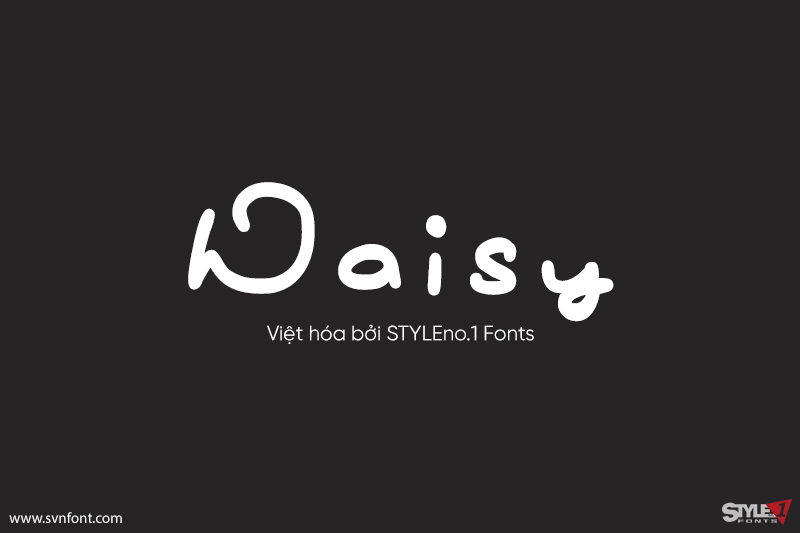
Tải Font Việt hóa SVN Daisy Miễn Phí: Tuyệt Chiêu Thiết Kế Tài Liệu Học Tập Chuyên Nghiệp
Trong thế giới thiết kế đồ họa và tài liệu học thuật, việc lựa chọn một Font Chữ phù hợp không chỉ giúp truyền tải thông điệp rõ ràng mà còn tạo nên dấu ấn thẩm mỹ riêng biệt. Đặc biệt đối với học sinh, sinh viên và giáo viên, những tài liệu cần sự hấp dẫn thị giác cao như bài thuyết trình hay luận văn tốt nghiệp, một bộ font đẹp là điều không thể thiếu. Hôm nay, chúng tôi sẽ giới thiệu chi tiết về Font Việt hóa SVN Daisy – một lựa chọn tuyệt vời cho mọi nhu cầu typography tiếng Việt.
Bộ font này đã nhanh chóng trở nên phổ biến nhờ sự kết hợp hài hòa giữa phong cách hiện đại và nét mềm mại, rất phù hợp cho các dự án sáng tạo. Việc sử dụng phiên bản đã được Việt hóa hoàn chỉnh giúp người dùng dễ dàng nhập liệu tiếng Việt với đầy đủ các dấu thanh mà không gặp lỗi hiển thị, đây là ưu điểm lớn so với các font quốc tế chưa được tối ưu.
Giới Thiệu Về Font Việt hóa SVN Daisy: Nét Chữ Mềm Mại Cho Mọi Thiết Kế
SVN Daisy thuộc nhóm font chữ script hoặc calligraphy nhẹ, mang lại cảm giác viết tay tự nhiên, thanh lịch. Nó được phát triển dựa trên bộ font gốc và được cộng đồng SVN (Style Việt Nam) tiến hành Việt hóa một cách tỉ mỉ. Mục tiêu của việc Việt hóa là đảm bảo font hiển thị hoàn hảo các ký tự đặc biệt trong tiếng Việt như ă, â, đ, ê, ô, ơ, ư mà vẫn giữ nguyên được tính thẩm mỹ và độ tương thích cao trên nhiều hệ điều hành và phần mềm khác nhau.
Font chữ này nổi bật nhờ các đường nét uyển chuyển, độ dày mỏng linh hoạt, tạo cảm giác sang trọng nhưng không quá cầu kỳ. Đây là lý do khiến Font Việt hóa SVN Daisy được ưa chuộng không chỉ trong thiết kế thiệp mời, bao bì mà còn trong các ấn phẩm giáo dục đòi hỏi sự tinh tế, từ các bài giảng cấp cao đến các ấn phẩm chuẩn bị cho kỳ thi tốt nghiệp THPT.
Đặc Điểm Nổi Bật Của Bộ Font SVN Daisy Gốc Và Phiên Bản Việt Hóa
Để hiểu tại sao SVN Daisy lại là lựa chọn hàng đầu cho các chuyên gia và học sinh đang chuẩn bị cho các kỳ thi hay dự án cuối cấp, chúng ta cần xem xét những đặc điểm kỹ thuật và thẩm mỹ của nó:
- Tính thẩm mỹ cao: Phong cách chữ viết tay, lãng mạn, rất phù hợp cho tiêu đề bài giảng, bìa sách, hoặc slide thuyết trình. Nó giúp tài liệu học tập trở nên sinh động và ít khô khan hơn.
- Khả năng ứng dụng linh hoạt: Mặc dù là font script, SVN Daisy vẫn duy trì độ rõ ràng cần thiết, cho phép nó được sử dụng ở nhiều kích cỡ khác nhau mà không làm mất đi vẻ đẹp vốn có, rất lý tưởng cho cả tiêu đề lớn và nội dung phụ chú.
Ứng Dụng Thiết Kế Đặc Trưng Của SVN Daisy Trong Giáo Dục
Đối với môi trường học đường, Font Việt hóa SVN Daisy mang lại nhiều lợi ích thiết thực, giúp nâng cao chất lượng trực quan của tài liệu. Học sinh cấp 3 có thể tận dụng font này cho việc thiết kế bìa tiểu luận, bài báo cáo hay poster dự án khoa học. Giáo viên có thể sử dụng font này cho tiêu đề các slide bài giảng để thu hút sự chú ý của học sinh, tạo sự chuyên nghiệp và độc đáo hơn so với các font mặc định nhàm chán.
Sự thanh lịch của font cũng rất phù hợp cho việc thiết kế các giấy chứng nhận, bằng khen, hoặc thiệp chúc mừng tốt nghiệp, tạo ra ấn phẩm lưu niệm có giá trị thẩm mỹ cao. Việc sử dụng font chữ đẹp, dễ đọc còn gián tiếp cải thiện trải nghiệm học tập và sự hứng thú của người tiếp nhận thông tin, giúp cho các bài thuyết trình trở nên ấn tượng và đáng nhớ hơn.
Tóm lại, Font Việt hóa SVN Daisy là một tài sản quý giá trong bộ sưu tập typography của bất kỳ ai đam mê thiết kế hoặc muốn nâng cao tính thẩm mỹ cho tài liệu học tập của mình. Sự kết hợp giữa nét chữ nghệ thuật và tính năng hỗ trợ tiếng Việt hoàn hảo đã giúp bộ font này chiếm được cảm tình lớn từ cộng đồng học sinh, sinh viên và nhà thiết kế. Hãy đảm bảo bạn tìm được phiên bản chất lượng, chuẩn xác và tuân thủ các quy tắc bản quyền khi sử dụng. Việc đầu tư vào một Font Chữ đẹp, chuẩn mực như SVN Daisy chắc chắn sẽ mang lại hiệu quả thị giác vượt trội cho mọi dự án, từ bài kiểm tra cuối kỳ đến luận văn tốt nghiệp.